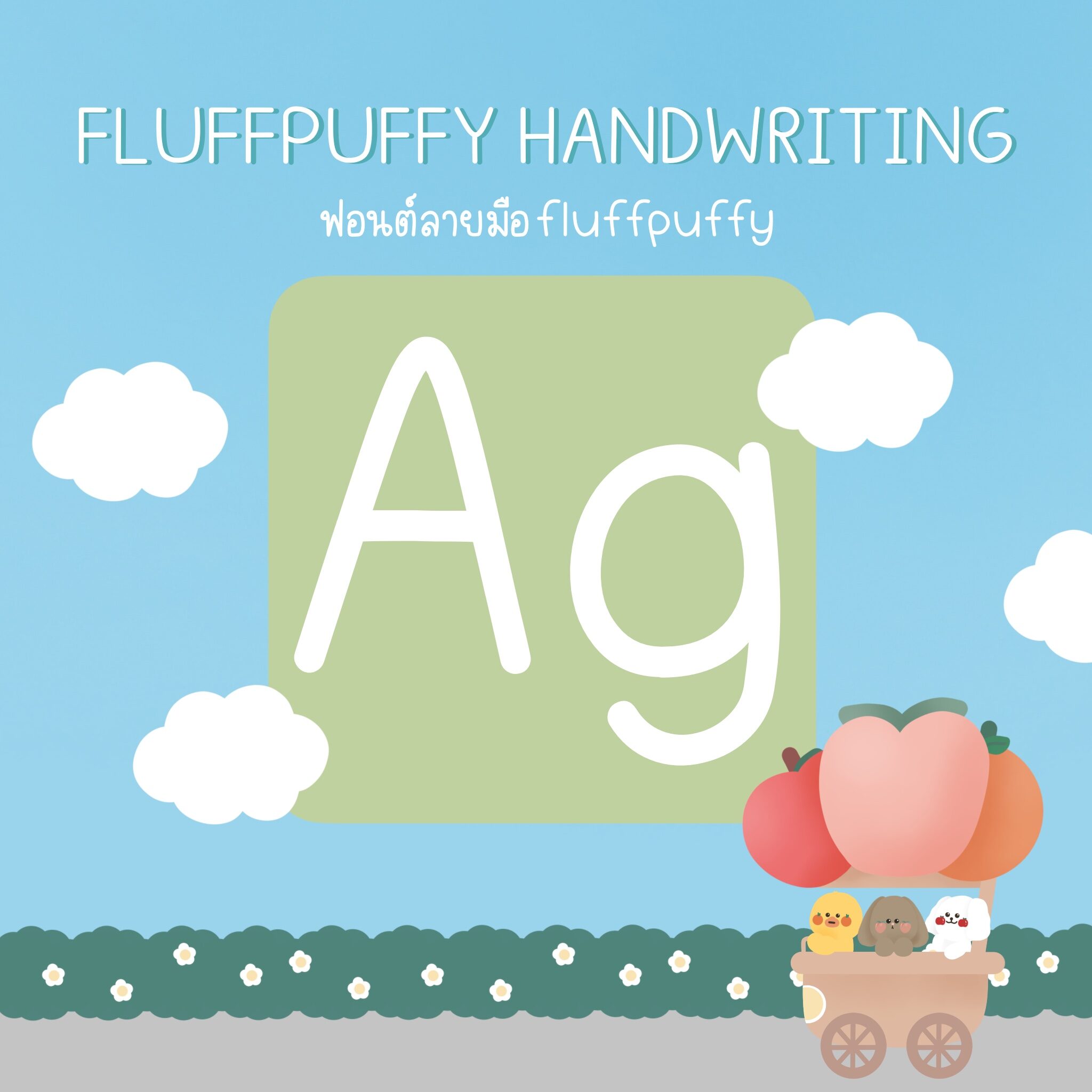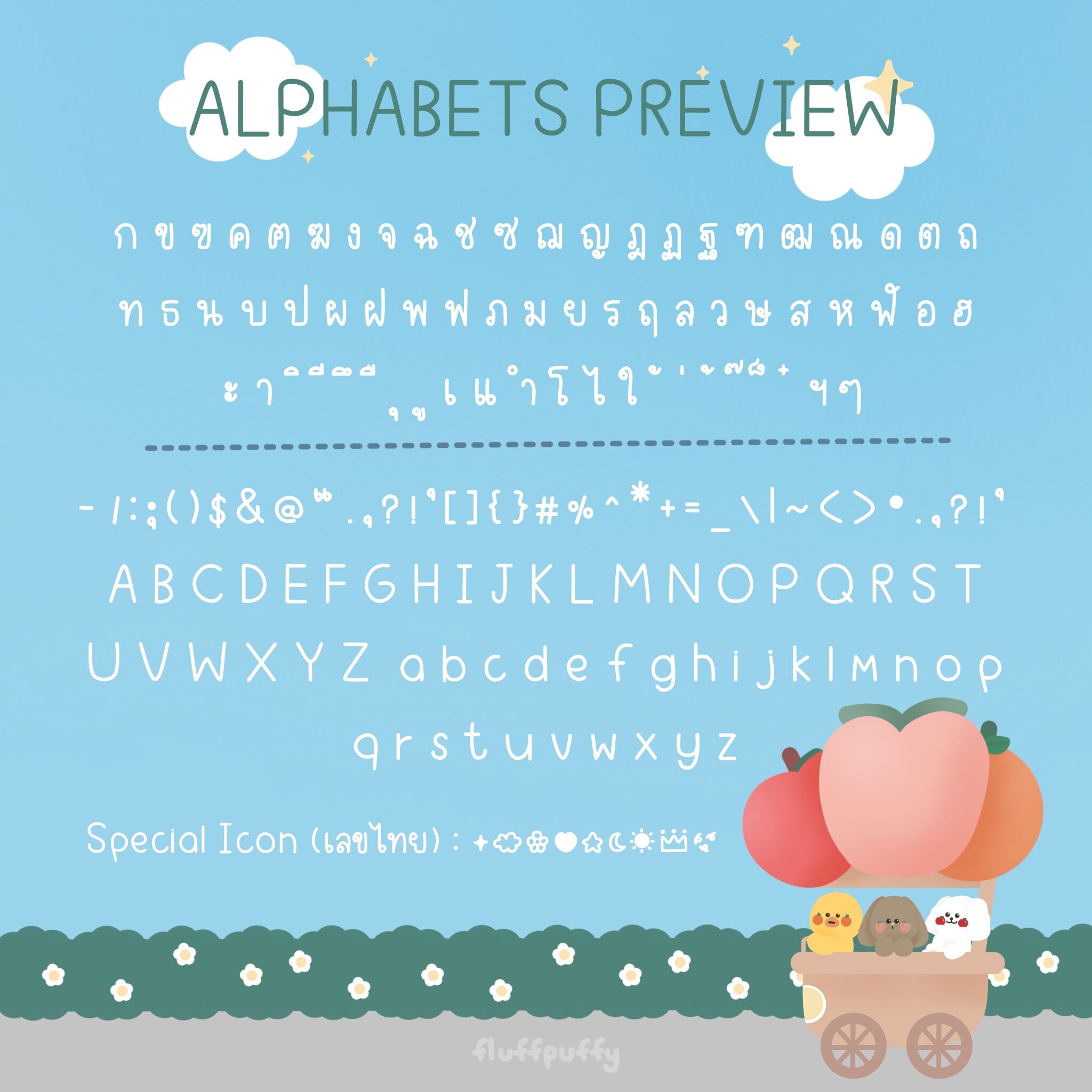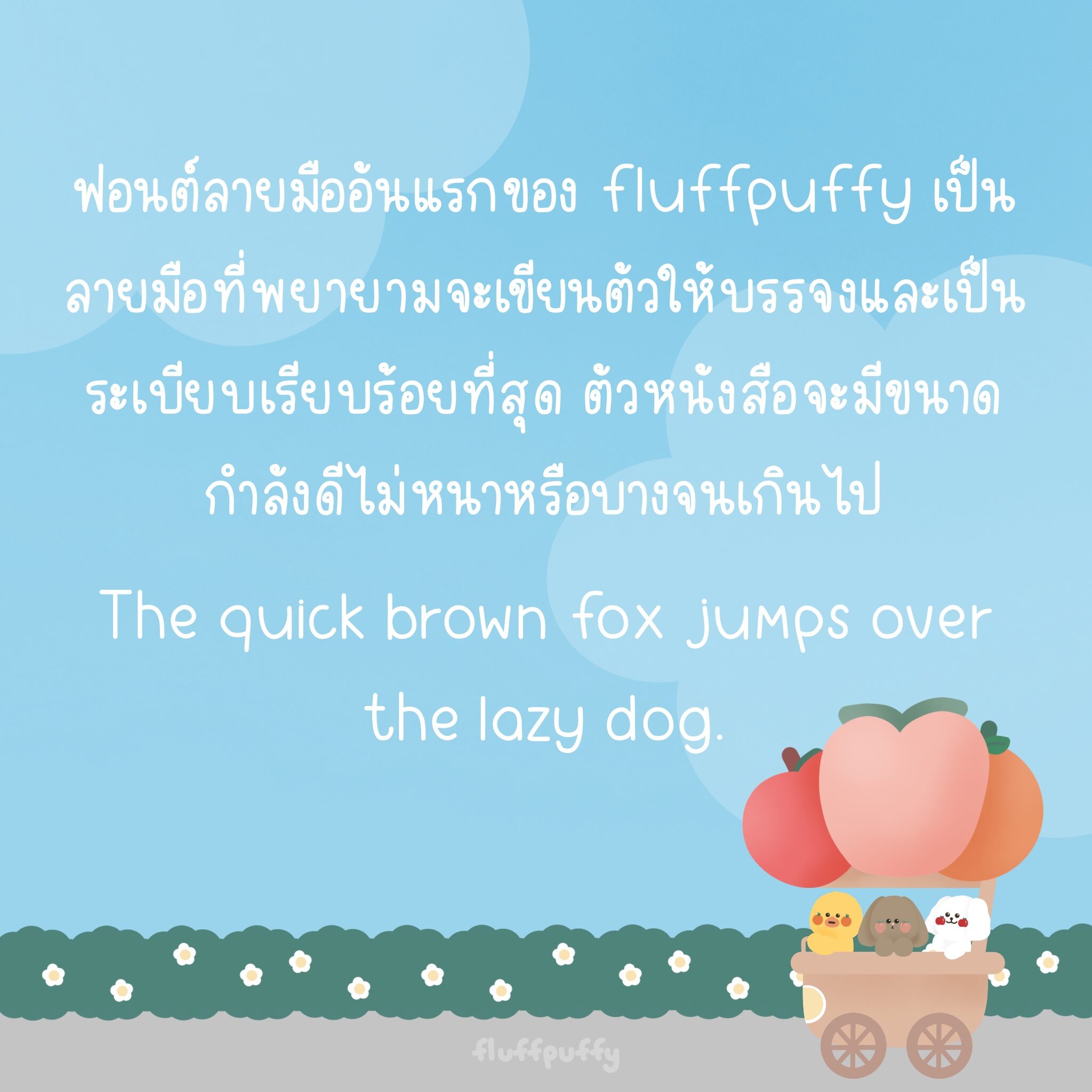
FLUFFPUFFY | FONT (Fluffpuffy Handwriting)
Font ลายมือ Fluffpuffy  เป็นลายมือที่เขียนตัวบรรจงเป็นระเบียบเรียบร้อย ตัวหนังสือจะมีขนาดกำลังดีไม่หนาหรือบางจนเกินไป สามารถใช้สำหรับทำ Artwork หรือพิมพ์งานที่ไม่เป็นทางการได้